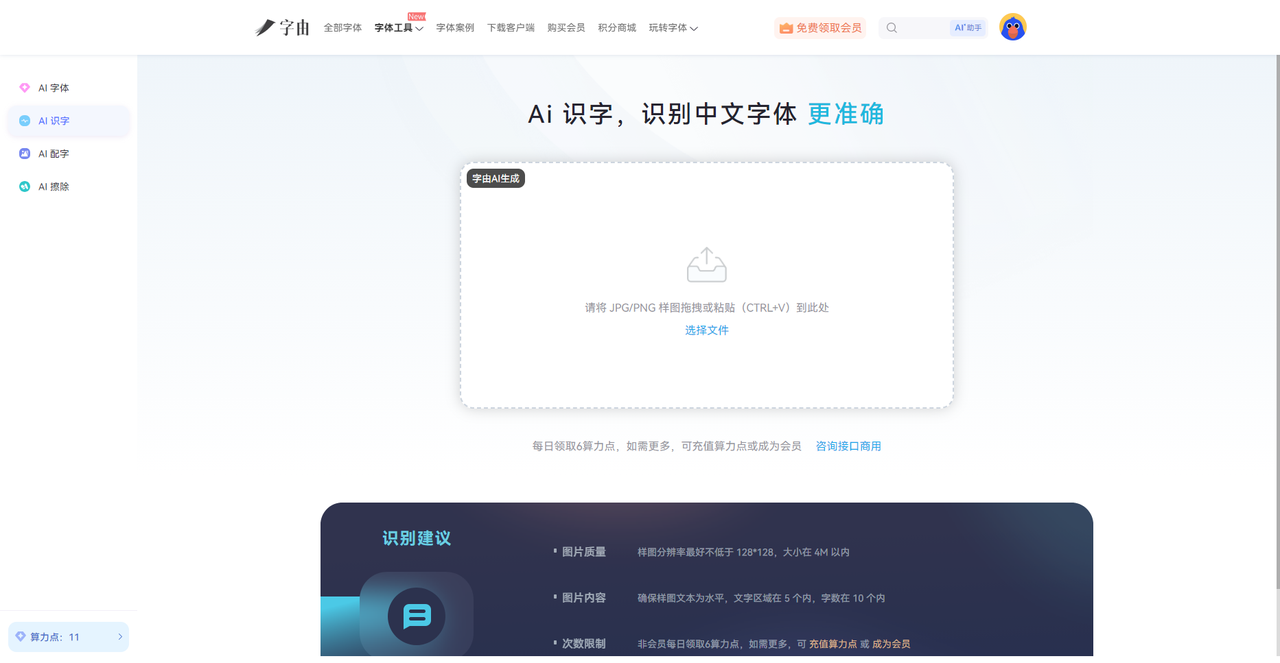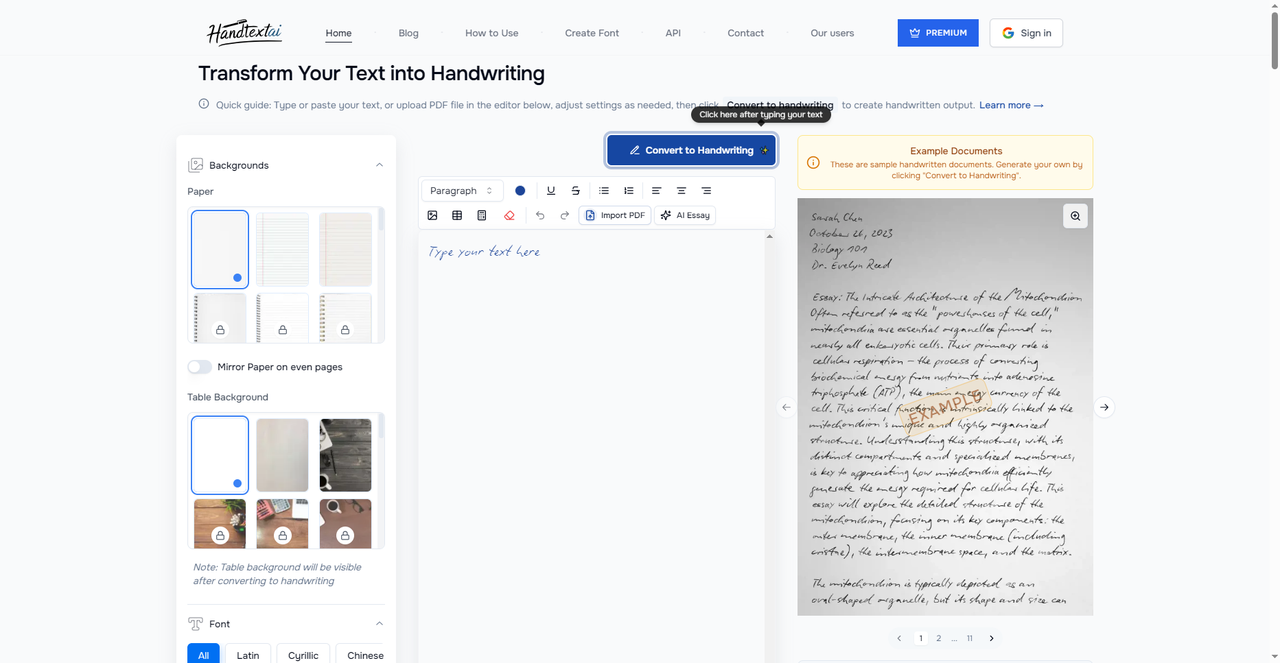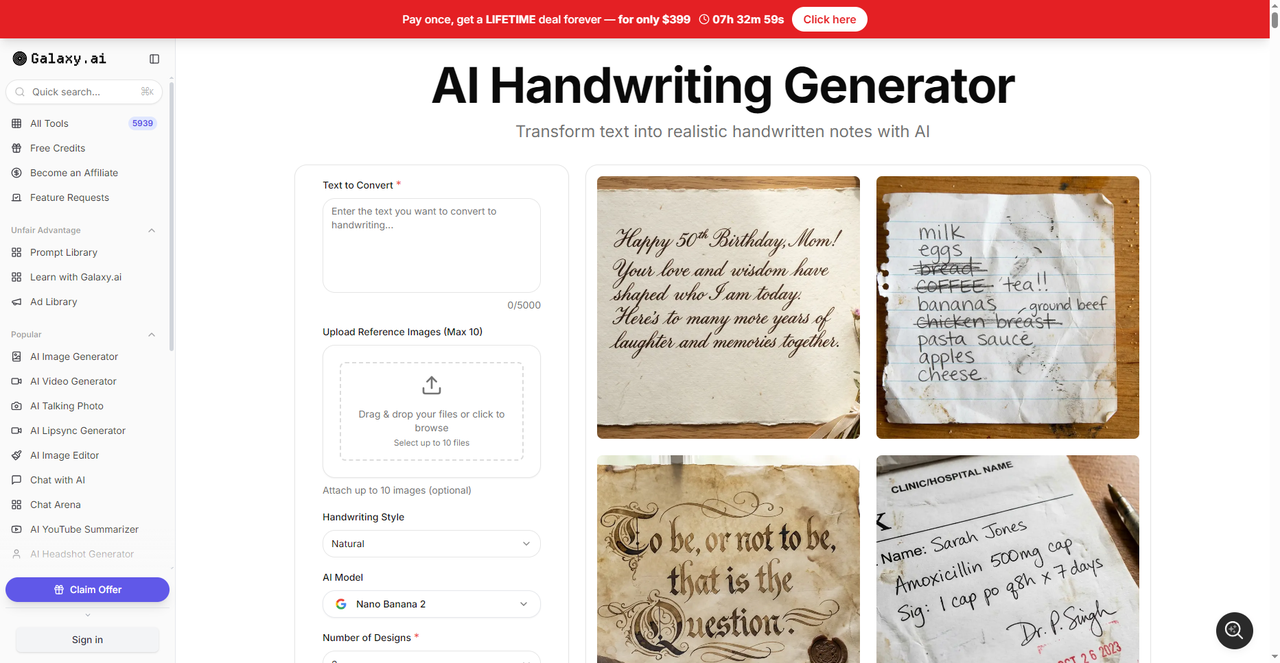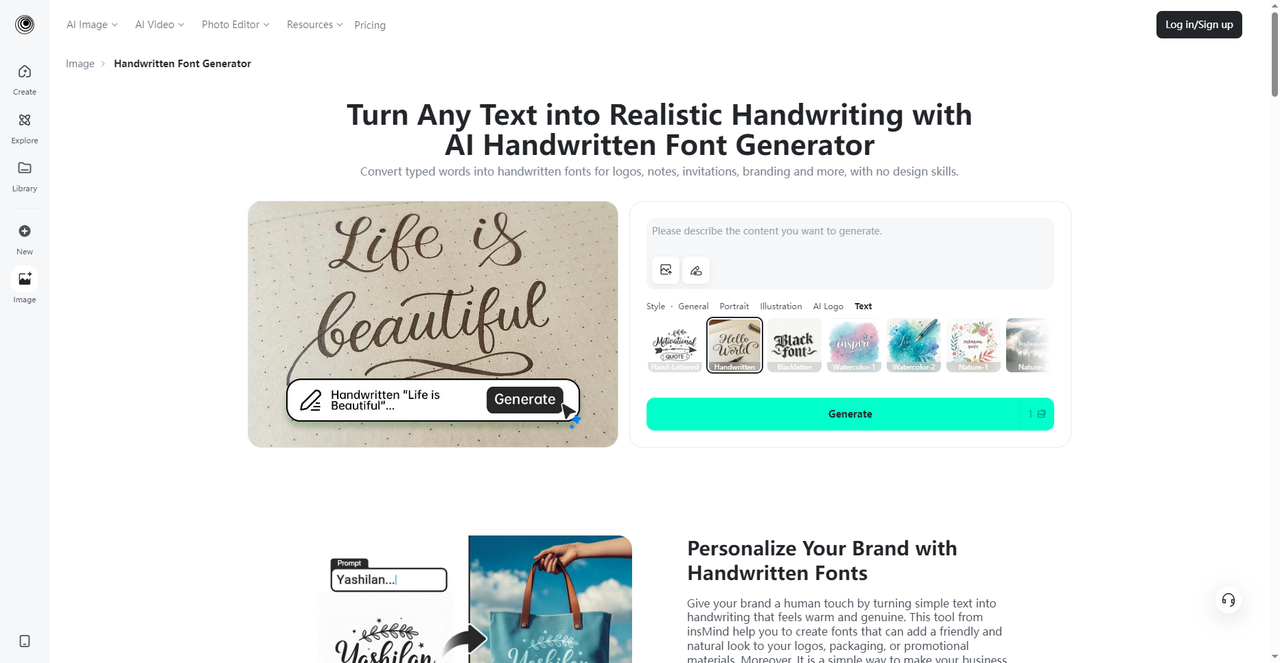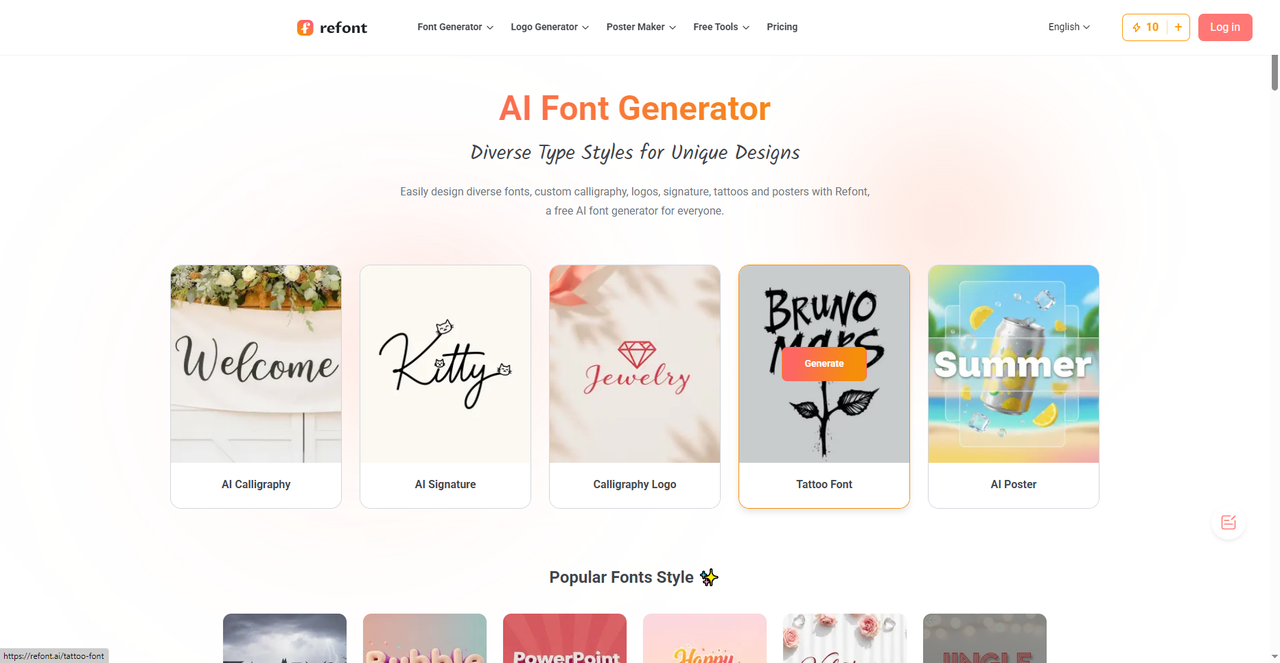
手写艺术字AI设计,输入文字就能用的5个工具推荐
不知道你有没有发现,那些能够第一眼就吸引力注意力的设计往往不是构图有多么精妙,而是在构图最上面的字体完美地应用到封面中,比如说咖啡店招牌上用着手写的艺术字,专辑里面飘逸洒脱的字体,又或者是一些手写的生日贺卡。这种带着手写特色的艺术字总能让死板的画面一下子活过来,带上人情味。以前如果想要设计出这种效果的话基本都是要花钱找设计师,但是现在随着AI 的发展,手写艺术字AI 设计工具让每个人都能轻松拥有专属的艺术字。
第一个要推荐的手写艺术字AI 设计工具是字由。字由的AI 字体功能可以直接生成各种风格的手写艺术字,但是除了AI 字体的功能字由还支持很多其他的实用功能,其中就有海量手写体库,如果AI 字体还不能满足你的话不放看看字由本身带的超大字体库。
言归正传,我会教大家如何用字由的AI 字体来制作手写艺术字 AI 设计,操作非常简单,以下是具体步骤:
• 打开AI字体入口:在字由客户端左侧导航栏点击【工具】→【AI字体】,或者从首页【字体工具】→【AI工具】进入。
• 选择手写风格模板:在模板库里找到“手写风”“书法风”等分类,或者搜索关键词“手写”“签名”“可爱手写”。模板包括流畅手写、儿童笔迹、复古花体等。
• 输入文字:点击“做同款”,输入你的文案,最好与模板字数一致。
• 一键生成:点击生成,等20-30秒就能得到高清手写艺术字图片。支持透明背景下载,直接用于设计。
除了AI 字体,字由还有很多其他的AI 工具能够辅助你做设计:
• AI识字:这是一个十分好用的工具,你可以上传带文字的图片,AI自动识别图中使用的字体名称,同时提供该字体的授权类型信息(免费商用/会员商用等),如果是字由站内收录的字体,直接提供使用入口,从识字到用字一站式完成。
• AI擦除:这个功能简直是修图神器,专门解决“想去掉图片上的文字又不想慢慢修”的问题。这个功能可以智能识别图片中的所有文字区域,智能识别图片中的所有文字区域。
• AI配字:这个功能对新手特别友好,解决“不知道用什么字体合适”的选择困难症。可以上传参考图片,AI识别图中元素(风景、人物、产品等),从海量字体库中推荐最适合该图片的字体风格
• AI字效:这个功能和AI字体有点像,但更侧重于“给现有字体加特效”。内置400多种字体特效模板,支持自定义调整特效参数。
这几个AI 工具简直不能太好用,对于我这种喜欢高效率的设计师来说完全是福音,以上的AI工具推荐在网页端使用,非常便捷。
2、HandtextAI
HandtextAI 是一款专注于将数字文本转换为逼真手写文档的手写艺术字AI设计工具。我推荐这个网站的主要原因还是它的文字转手写的功能比较强大,并且也确实依赖于AI 设计,并且它还支持拉丁、西里尔、中文等多种语言,满足全球化需求。关于字体,它内置了90多种手写字体,还可以上传自定义字体,总会有你想要的。这非常适合商务人士制作个性化信件,也是输入文字就可以使用了!
3、AI Handwriting Generator
AI Handwriting Generator 是一个更智能的手写艺术字AI设计工具,它允许你上传自己的手写图片作为参考,让AI模仿你的笔迹生成新文字。如果你对它一开始提供的AI模型不感兴趣的话,还可以选择不同的AI模型(如Nano Banana 2),调整生成效果。而且从图中的右侧看,我们可以知道的是这个网站可以一次可生成多个设计方案,提供了更多的选择。
4、insMind AI Handwritten Font Generator
insMind 推出的这款手写艺术字AI设计工具,主打品牌个性化和社交媒体内容创作。我之所以推荐这款,是因为它的核心亮点:品牌应用。谁说手写艺术字只能用作写信的?为Logo、包装、宣传材料添加手写字体,让品牌更有温度和亲和力,手写字更擅长做这件事。而且它强调“no design skills”,适合所有用户。
5、Refont AI Font Generator
Refont 是一个综合性的AI字体生成平台,涵盖手写、书法、签名、纹身字体等多种风格。它被超过100万创作者和多家媒体认可。它主要包括以下几个主要功能:
• AI Calligraphy:生成优雅的书法字体。
• AI Signature:设计个性化签名。
• Calligraphy Logo:制作书法风格的Logo。
• Tattoo Font:纹身字体设计。
• AI Poster:一键生成海报文字。
都是很实用的AI 字体生成工具,而且Refont 提供了多样化的手写艺术字AI设计方案,无论你是设计师还是普通用户,都能找到合适的工具。
今天介绍的这5 款手写艺术字AI设计工具基本上覆盖了你所需要的所有功能,但是字由可以做到结合后面四款的优势,因为它不仅有AI生成和海量手写体库,还能一键应用到设计软件中,是设计师的得力助手。如果你想要一款漂亮的手写艺术字AI 字体,那么可以来字由试一试,选个模板,30 秒就能拿到可用的手写艺术字,再也不用为手写字发愁。